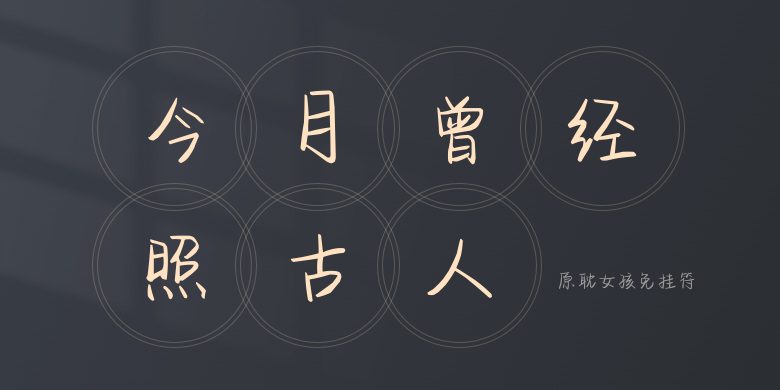
原耽女孩免挂符
原耽女孩免挂符,这款字体结构工整、笔画清晰,兼顾美观与易读性,适用于标题、正文、海报、包装、LOGO 等多种场景。字形优雅稳定,风格百搭耐看,适配日常排版与创意设计,让文字呈现更舒适、更具质感。原耽女孩免挂符一笔一画,皆是细节,以均衡的比例、流畅的线条打造舒适视觉体验,字形端正大气,风格简约现代。无论是商业设计、品牌宣传还是日常排版,都能轻松驾驭,让文字更有格调与力量。原耽女孩免挂符字体下载。